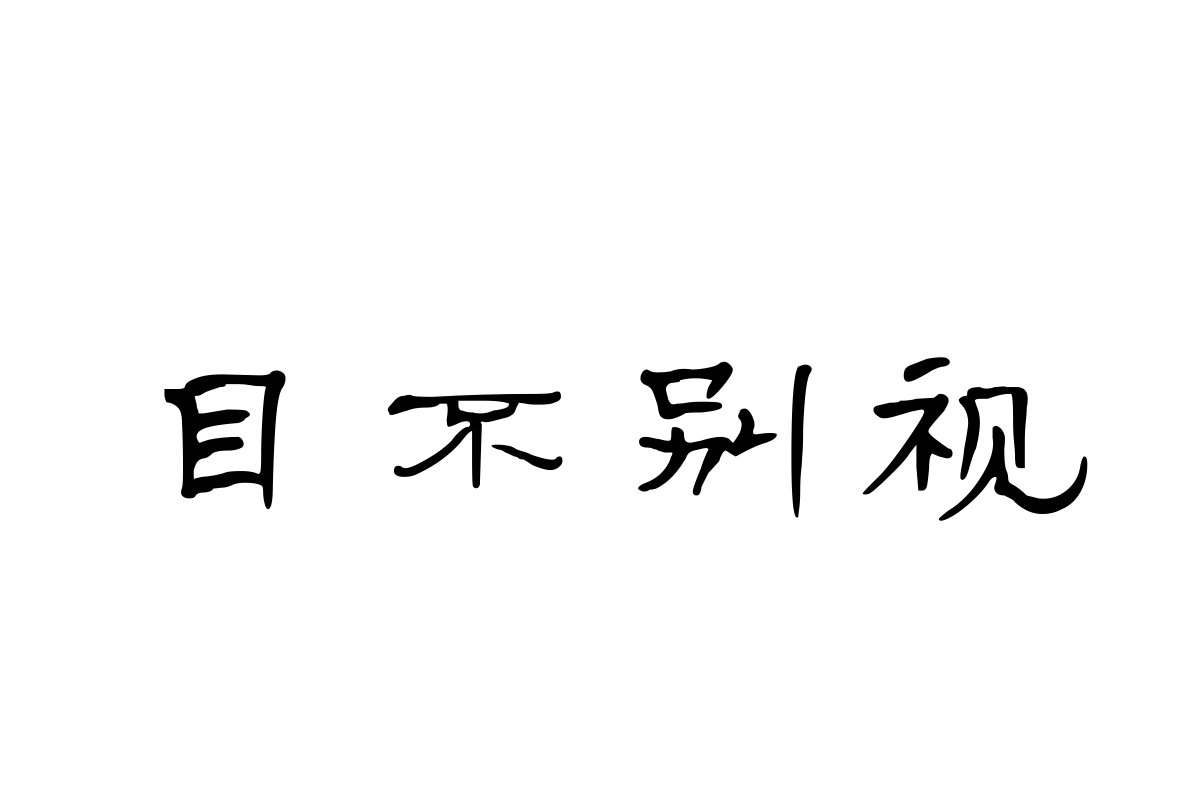
三极文明隶书字体是一套基于传统隶书风格,融入现代元素设计的中文字体。它由三极文化公司设计,旨在为现代设计提供一种新的视觉语言。
该字体具有以下特点:
– 字形规整,笔画流畅,易于阅读和书写。
– 结合了传统隶书的笔触和现代平面设计的元素,既有古典韵味又不失现代感。
– 适用于广告、标识、海报、报纸、杂志等多种场景。
– 支持多种字重和排版方式,满足不同设计需求。
总之,三极文明隶书字体是一款具有独特风格和广泛应用前景的中文字体。